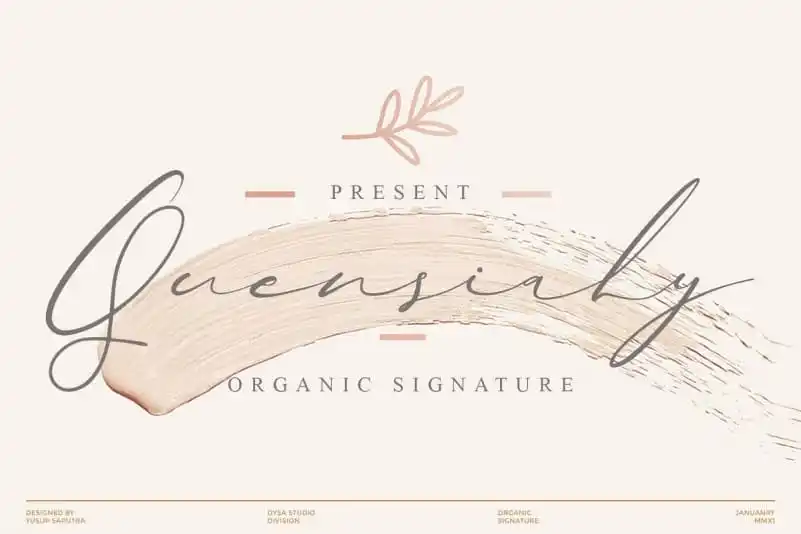
Quensialy Script Font – Download Grátis
A Quensialy Script Font é uma elegante tipografia moderna com um estilo chamadoquinho repleto de ritmo. Ela foi projetada para imitar a experiência de escrever a mão com um canuto, capturando sua característica mistura de gotículas e borrões de tinta. Esta fonte é perfeitamente adequada para seu próximo projeto de branding ou criação de identidade visual da empresa. Com suas bordas naturais e linhas delicadas, a Quensialy transmite um estilo autêntico de arte manual. Perfeita tanto para nomes profissionais quanto para gráficos pessoais, ela oferece um toque moderno e criativo que certamente se destacará em qualquer projeto. Seja no design da sua empresa ou na criação de conteúdo online, a Quensialy Script Font é uma escolha perfeita para aqueles que buscam transmitir seu estilo com elegância e personalidade.